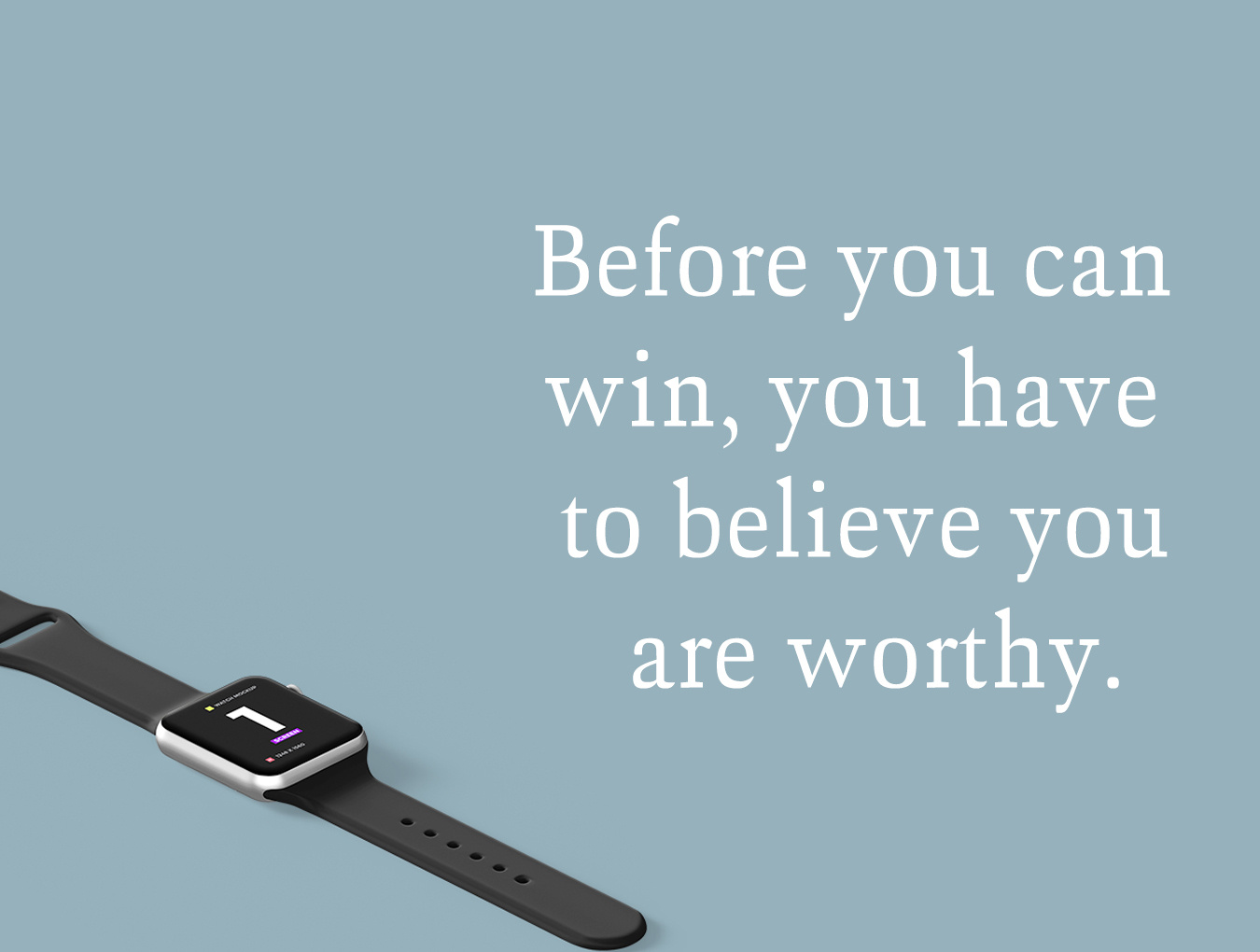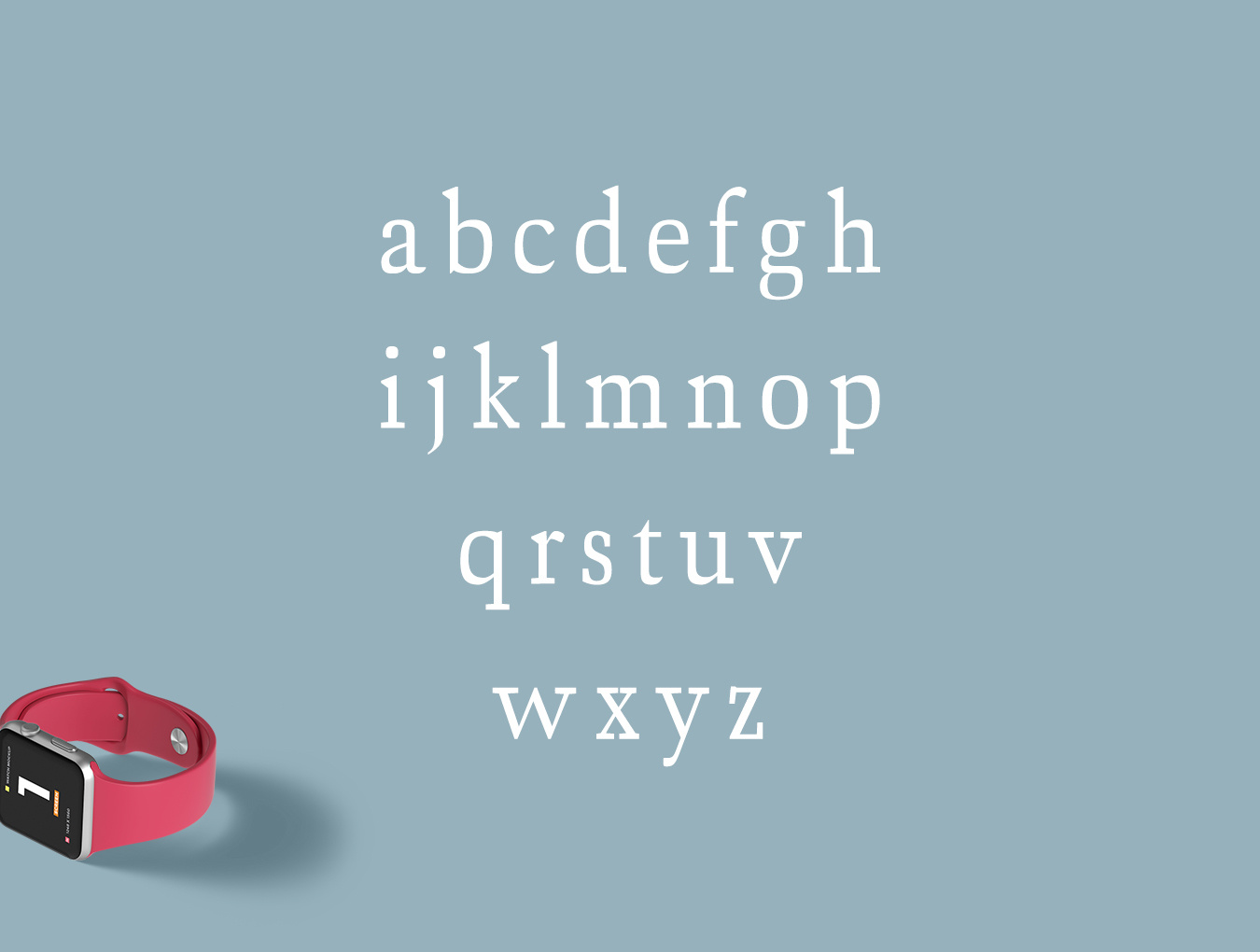
Ailish Slab Serif 3系列字体,Ailish Slab Serif
Ailish Slab Serif Typeface是一套包含3个重量,适合制作创意展示。它是我们商店中可爱而独特的平板衬线字体,让您可以让每个单词看起来都非常时尚!它最适合现代/干净的设计,标识,标题,横幅和模板等。如果你想尝试一个优雅的外观,它看起来华丽的所有大写间距,或美丽的大写和小写字母为完全永恒的东西。